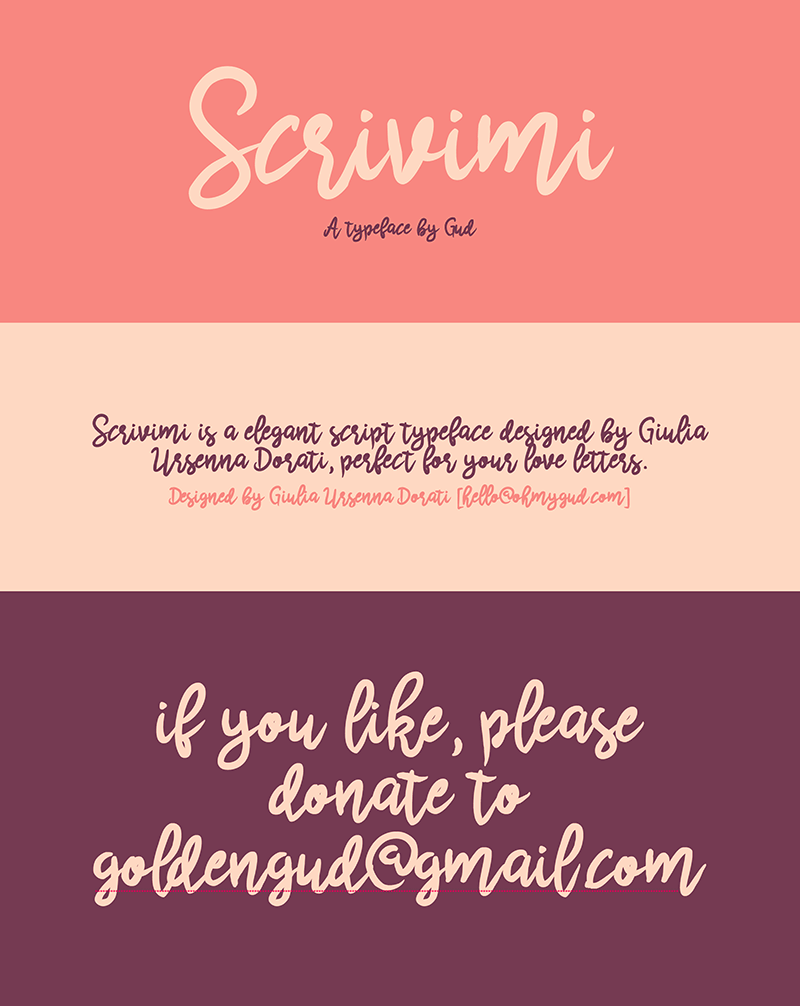
A fonte Scrivimi é uma elegante tipografia script criada por Giulia Ursenna Dorati, perfeita para seus cartões de amor delicados e charmosos. Se você gosta deste design, nós incentivamos a doar através de . Acreditamos que essa fonte vai tornar sua escrita mais encantadora e sofisticada, especialmente em cartas e mensagens personalizadas. Para o designer Hamilton, a fonte Scrivimi foi adaptada para um estilo handwritten. Este design fluido e delicado pode ser ideal para criar cartões de aniversário ou outros documentos pessoais com uma sensação única e autêntica. Esse design elegante é perfeito para aquelas criações que exigem um toque especial e sofisticado, criando textos atraentes em diferentes formatos. Hamilton tem demonstrado talento na adaptação de fontes elegantemente script, mantendo o charme e a sofisticação do original enquanto adiciona sua própria visão única. Esta é uma oportunidade para explorar um novo modo de expressar-se através da escrita, fornecendo um estilo que pode transformar simples mensagens em experiências memoráveis e únicas.